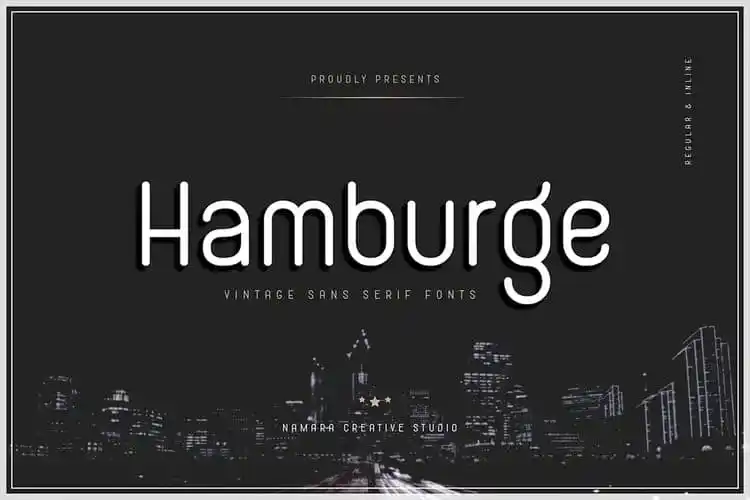
Hamburge Sans Serif Font – Fonte Grátis
Hamburge Sans Serif Font
A Hamburge Sans Serif é uma fonte sem serif minimalista criada pelo Namara Creative Studio que se destaca por sua forma côncava e clássica. Perfeita para logos, também combina perfeitamente com qualquer situação. Inspirado no minimalismo contemporâneo, esta fonte oferece um design limpo, limpo e versátil. Com suporte a maiúsculas, minúsculas, números e caracteres especiais, ela se adapta a uma variedade de idiomas. Ideal para criar identidades visuais modernas e minimalistas, é perfeita para quem busca uma fonte sem serif que seja clara, clean e flexível. Sem dúvida um excelente complemento para qualquer projeto gráfico que valorize elegância simples e sofisticação.